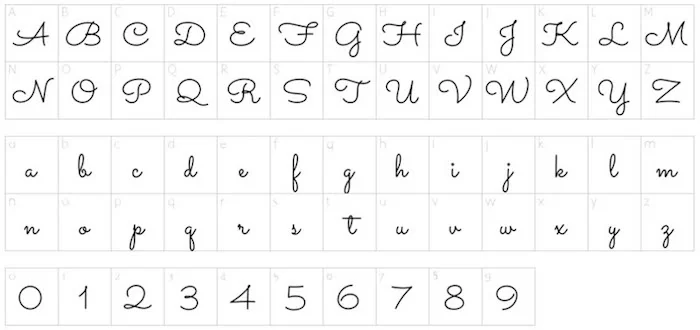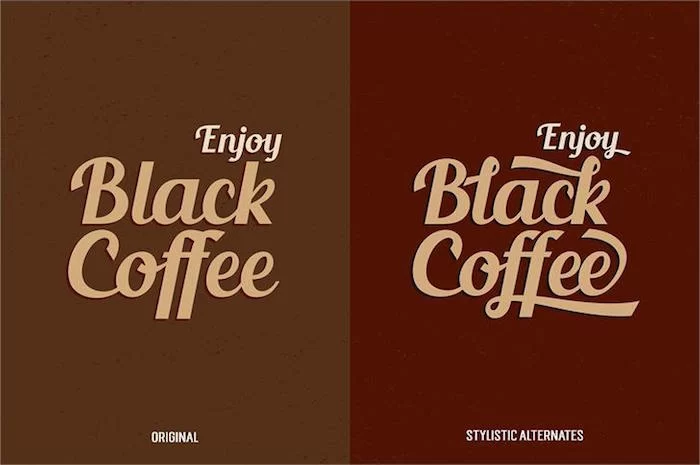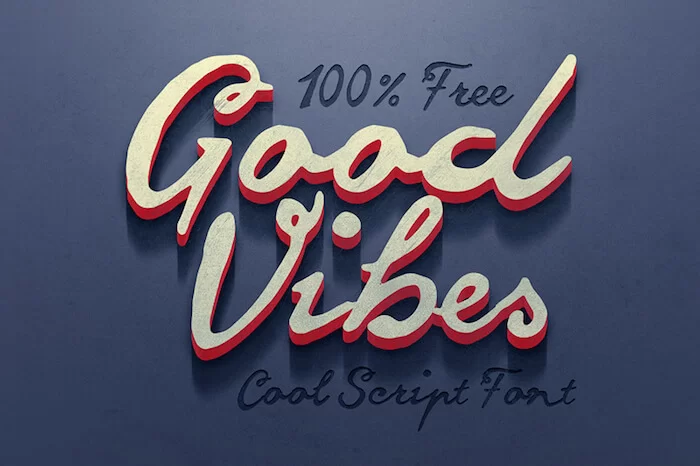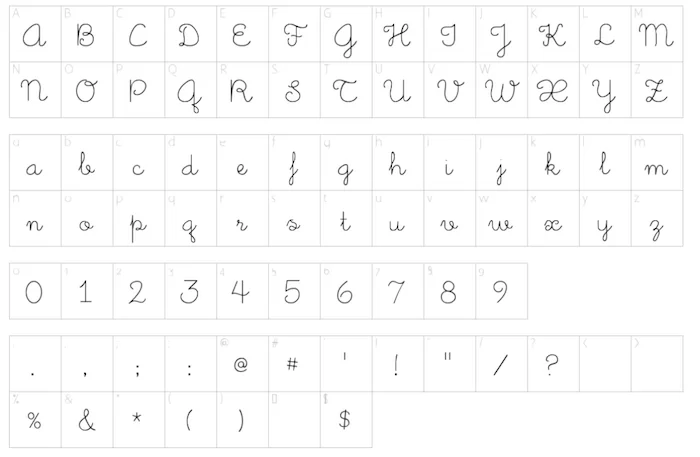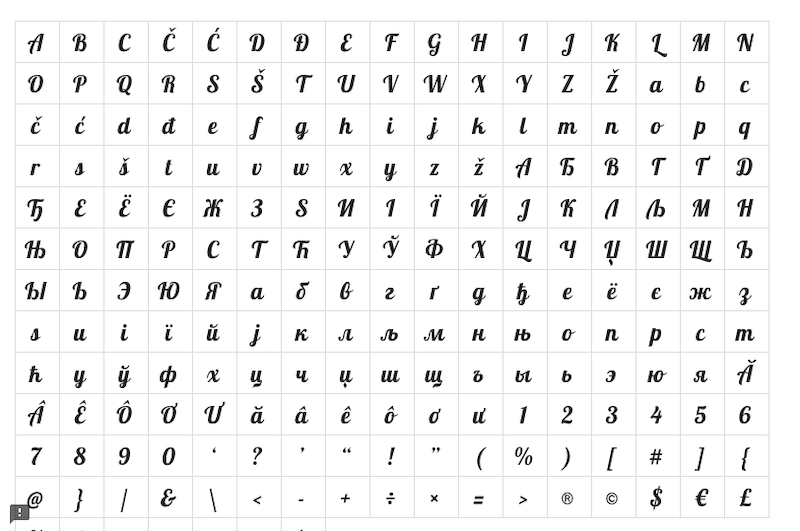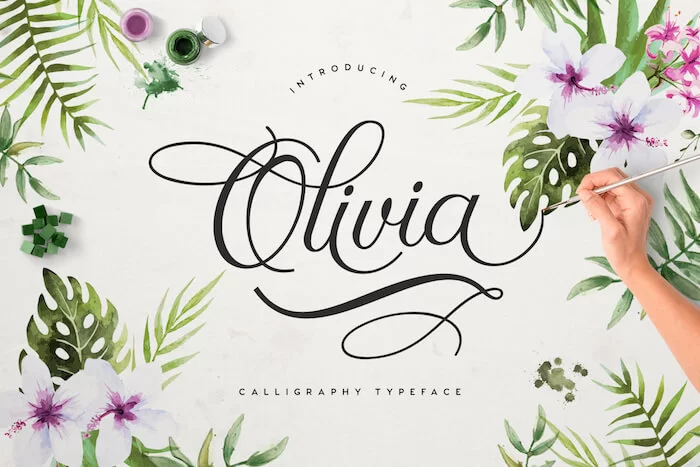
Las 50 mejores fuentes gratuitas de caligrafía y cursiva para diseñadores
Publicado: 2023-01-11La mejor caligrafía gratuita, fuentes cursivas que puedes usar en tu proyecto. La tipografía es uno de los factores más importantes cuando se trata de diseño, y aquí tenemos algunas de las mejores opciones de fuentes.
En otras palabras, podemos representar las fuentes cursivas como fuentes Script o fuentes escritas a mano que le darán una sensación natural y atractiva a su diseño.
Ya hemos enumerado las mejores fuentes de script donde encontrará excelentes opciones de fuentes. Las fuentes cursivas están ahí desde hace mucho tiempo y seguirán siendo una parte muy importante incluso de los diseños modernos.
En general, vemos el uso de fuentes cursivas en novelas, cartas y otros diseños que quieren usar el tipo de fuente manuscrita.
El uso de fuentes cursivas es común entre los artistas del tatuaje y el arte corporal. Ya hemos publicado un artículo para mostrar las mejores fuentes de tatuajes donde también encontrarás hermosas fuentes cursivas.
Hemos estado usando las fuentes cursivas desde nuestros días escolares y estas fuentes son las más relevantes incluso hoy en día. Y la mejor parte está ahí, hay una serie de fuentes increíbles para encontrar fuentes cursivas gratuitas que puedes descargar y usar en tus proyectos.
¿Qué son las fuentes cursivas?
Las fuentes cursivas son generalmente fuentes de escritura con letras unidas. Hemos estado usando fuentes cursivas durante mucho tiempo y sigue siendo uno de los tipos de fuentes más utilizados.
Las fuentes cursivas son las mejores opciones para proyectos creativos, diseños de logotipos y cualquier tipo de escritura que necesite una sensación atractiva.
Las fuentes manuscritas se consideran fuentes cursivas y difieren según el estilo y la complejidad de la escritura.
Las fuentes cursivas se utilizan más ampliamente para crear fondos de pantalla, eslóganes publicitarios, tarjetas de felicitación, vallas publicitarias, diseños gráficos y proyectos similares.
Entonces, sin más demora, echemos un vistazo a algunas de las mejores fuentes cursivas gratuitas.
Hermosas fuentes cursivas gratuitas
Fuente Arizona
Arizonia es una hermosa fuente moderna que se puede usar para cualquier escritura. Puede usar esta fuente para cualquier cartelera, proyectos relacionados con publicidad, tarjetas de felicitación o incluso para diseños de logotipos.
Fuente cursiva Noelan
La fuente Noelan del equipo Ndroadv es de uso gratuito para uso personal y comercial. La fuente se ve hermosa en cualquier fondo.
Puede usar esta fuente incluso para crear el logotipo de su empresa, ya que se ve moderno y moderno, y podrá crear un diseño único con esta fuente.
Guión Variane
Una fuente Cursive Script muy atractiva que hará que tu proyecto se destaque. No importa dónde esté utilizando esta fuente, su escritura, cualquier logotipo, restaurante o nombre comercial, o cualquier otro proyecto; esta fuente hará que se vea hermosa.
Cursiva de quinto grado
Crea un diseño vintage perfecto con esta hermosa fuente retro. La fuente es de uso gratuito para cualquier proyecto gratuito o comercial.
Allura
Allura es una fuente cursiva que es fácil de leer y se ve hermosa en cualquier fondo.
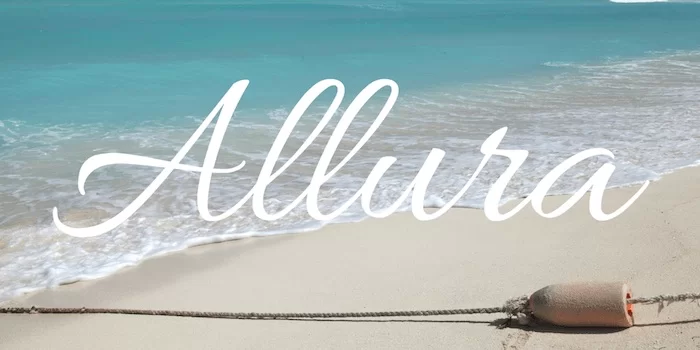
Fuente cursiva pesada Moonface Script
Una hermosa fuente de escritura para diseños de logotipos y otros requisitos de escritura similares. Puede echar un vistazo a la fuente y cómo se ve en diferentes fondos. La fuente aporta instantáneamente una sensación especial al aspecto general de cualquier palabra.
Fuente cursiva gratuita Varsity
Si está buscando una fuente cursiva muy atractiva, eche un vistazo a Varsity Font, una fuente tipográfica de la vieja escuela con un toque masculino.
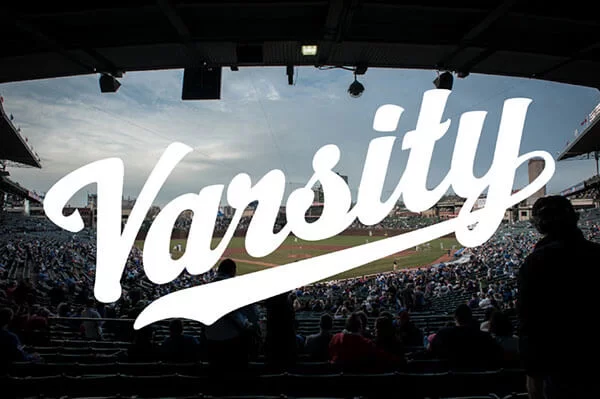
Fuente AlGhifari
AlGhifari Font es de uso gratuito para un proyecto personal, así que verifique la licencia antes de usarla para cualquier proyecto comercial.
AlGhifari es un tipo de letra caligráfico de excelente aspecto con bordes afilados que seguramente hará que su proyecto se vea muy profesional.
Fuente Acratica
Otra fuente caligráfica que es gratuita solo para uso personal. Esta es una tipografía manuscrita muy atractiva que hará que tu escritura se vea genial.
Puede usar esta fuente para cualquier logotipo, sus citas, escritura general, así como para cualquier proyecto en línea.
Fuente de galletas
Cookie Font es libre de usar Cursive Font para fines personales y comerciales. Esta es otra hermosa fuente manuscrita de estilo antiguo.
Belinda
Belinda, una fuente de escritura de pincel vintage muy atractiva hará que su diseño sea muy atractivo. Puede usar esta fuente para cualquier guión o crear un logotipo para su proyecto.
Fuente Monique Script
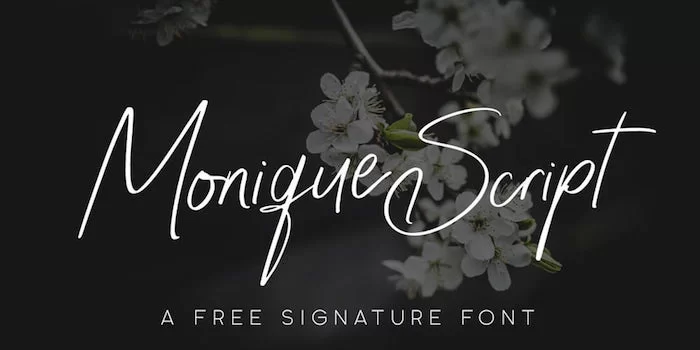
última palabra